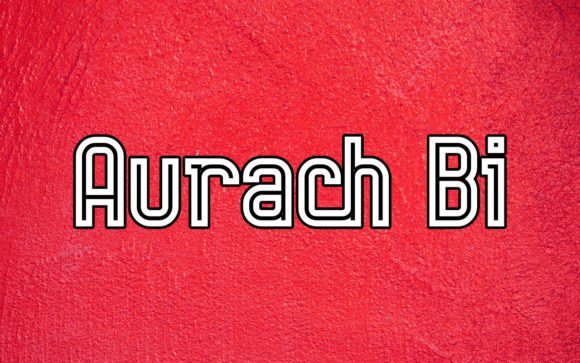
Aurach Bi, tipografía moderna de doble línea para display
Aurach Bi es una fuente de display audaz y limpia, diseñada para dar a tus proyectos creativos un carácter impactante, moderno y retro. Sus letras gruesas y geometría minimalista la hacen versátil e impactante, perfecta para diseños donde la claridad y la presencia son importantes. Ya sea que estés construyendo una marca, diseñando merchandising o creando materiales promocionales, Aurach Bi ofrece un estilo tipográfico refinado y audaz que destaca.
Aurach Bi combina una legibilidad nítida con un diseño limpio, lo que la hace ideal para logotipos, merchandising, carteles y branding que busca causar impacto. Su geometría sencilla garantiza que el texto se mantenga nítido y legible incluso en tamaños pequeños o grandes, lo que la hace útil en diversos medios. Al ser una fuente gratuita con licencia compatible (para uso personal y comercial), es una forma rentable de añadir un aspecto profesional y distintivo a sus productos creativos.
| Característica | Aurach Bi | Fuente genérica Clean Sans A | Fuente de visualización retro genérica B |
| Estilo / Vibra | Pantalla moderna y retro, audaz y limpia | Sans-serif neutra, minimalista y moderna | Expositor decorativo retro o vintage, estilizado. |
| Mejor caso de uso | Logotipos, marca, merchandising, carteles, packaging de estilo limpio | Texto del cuerpo, interfaz de usuario moderna, marca minimalista | Carteles estilizados, marcas vintage, impresiones decorativas. |